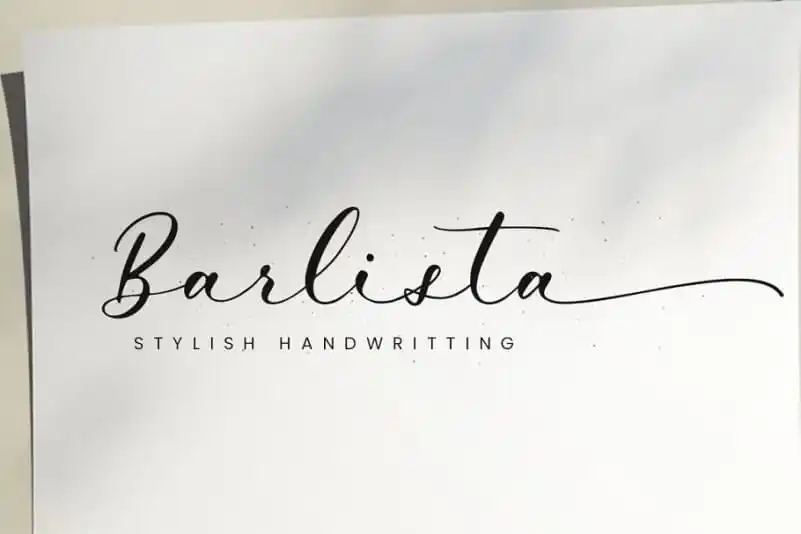
A Barlista Calligraphy Font é uma elegante fonte script que oferece um estilo de escrita artesanal e naturalmente atrativo. Ideal para aplicar em criações criativas, desde invições até embalagens, ela possui um toque moderno e feminino que faz dela a escolha perfeita para diversos tipos de projetos. Sronstudio é o designer responsável pela criação desta fonte de caligrafia linda, perfeitamente adaptada para trabalhos como decorações de eventos, postagens nas redes sociais, propaganda, embalagem de produtos e até mesmo em marcas únicas. Seja você um profissional de design ou simplesmente alguém que quer adicionar um toque artístico a seus projetos pessoais, a Barlista Calligraphy Font tem o que você precisa para dar vida à sua ideia única.